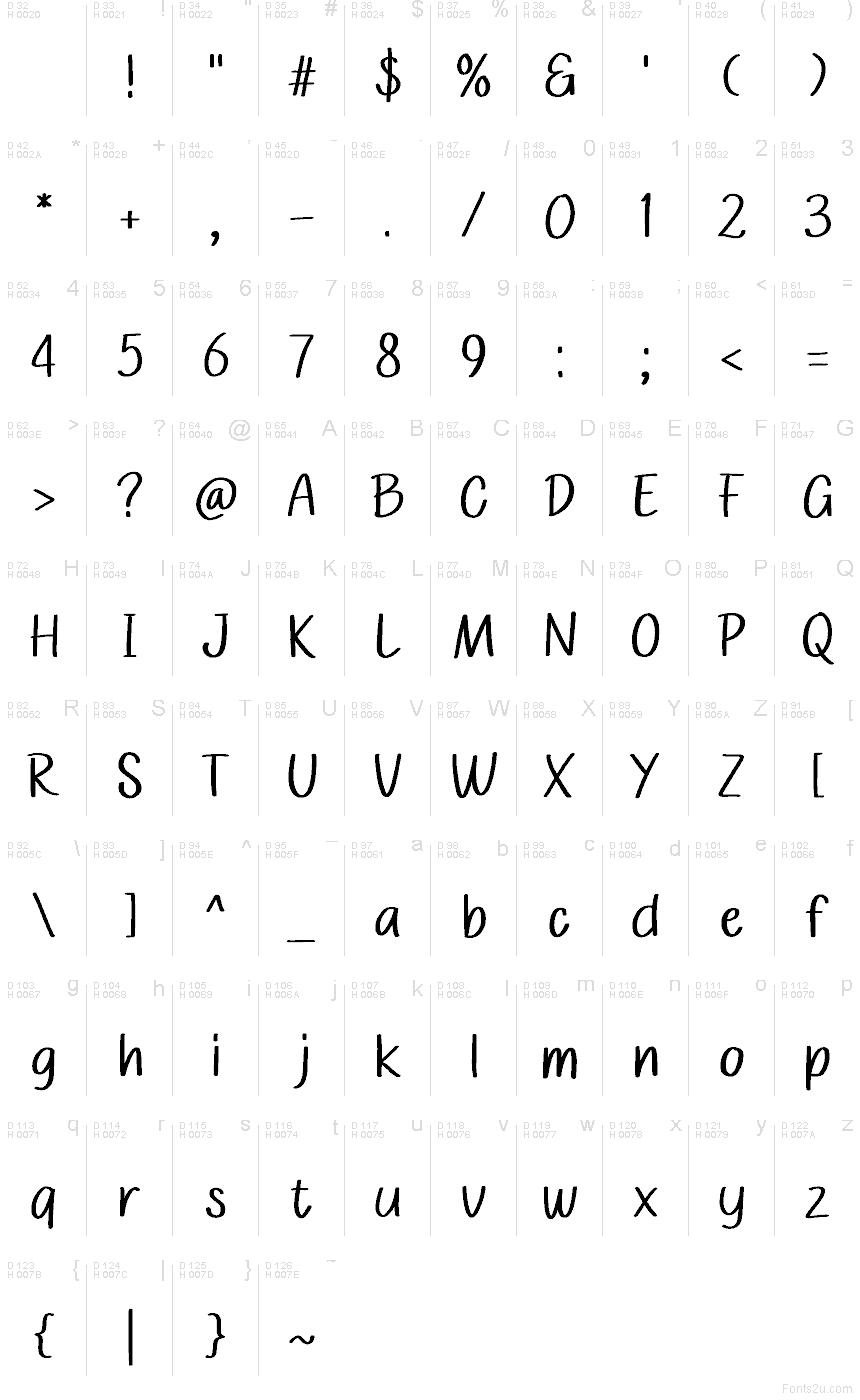
Hope Cartoon
Hope Cartoon від Hello Good Studio — це безкоштовний рукописний шрифт із невимушеними лініями, що нагадують маркер, та округлими, злегка нерівними формами. Літери виглядають наче намальовані одним рухом, із м’якими вигинами, простими з’єднаннями та природним ритмом, що позбавляє шрифт механічної жорсткості.
Hope Cartoon чудово підходить для логотипів, листівок, цитат у графіці, дитячого пакування та дописів у соцмережах, де потрібен дружній, «живий» рукописний акцент. Неформальний штрих та вільний інтервал надають роботам індивідуального, скетчевого характеру, зберігаючи при цьому охайність.